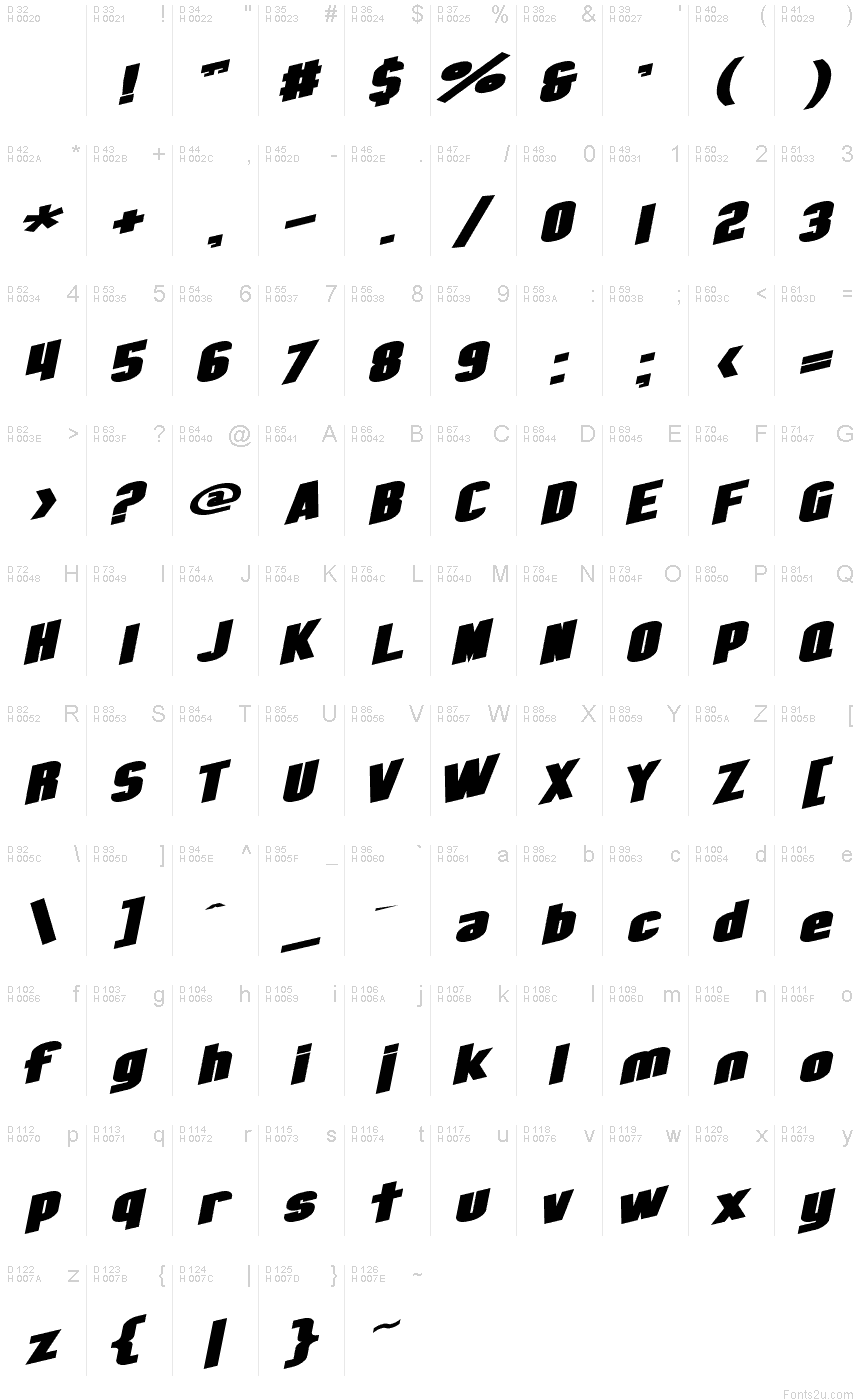
SF Obliquities Extended Bold od ShyFoundry to nowoczesny, ukośny krój typu display o zdecydowanym, technologicznym charakterze. Litery są mocno pochylone i sprawiają wrażenie wyciętych z szerokich, ciężkich kształtów, a ostre przekątne i ścięte rogi nadają mu szybki, zwarty i lekko futurystyczny rytm.
Świetnie sprawdzi się w brandingu gamingowym i sportowym, nagłówkach plakatów, oprawie muzycznej, planszach tytułowych i opakowaniach, gdzie potrzebny jest efekt ruchu bez popadania w pełną fantastykę naukową. Jako darmowy font, doskonale nadaje się też do krótkich haseł reklamowych, grafik eventowych i szkiców logo, bo wyraźne nachylenie i masywna sylwetka robią duże wrażenie przy użyciu zaledwie kilku znaków.
SF Obliquities Extended
ShyFoundry
Derek Vogelpohl